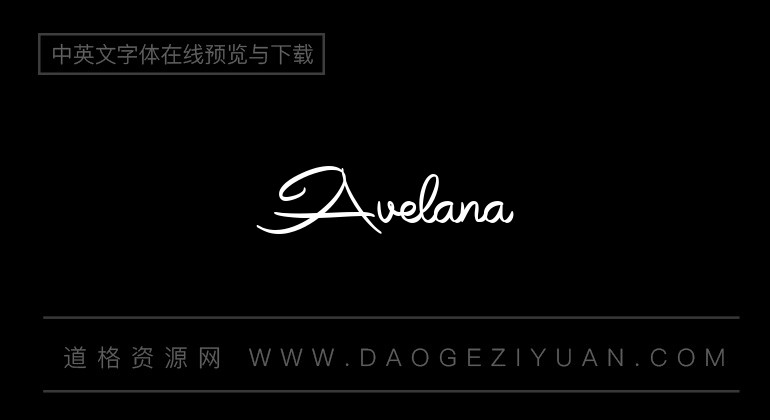
Avelana
Avelana是一种优美而现代的手写风格字体,设计师为其注入了自然、柔和、优雅的感觉。它是一种非常干净、可读性极高的字体,适用于各种设计用途,包括印刷品、品牌标识、包装设计、海报和广告等。Avelana字体家族包括正常、粗体、斜体和粗斜体四个字体样式,可以灵活地运用在设计中。总的来说,Avelana是一种非常适合那些需要表达优雅、简洁和现代感的设计项目的字体。
Avelana是一款非常不错的手写艺术字体,具有很好的视觉感,适合于文化类的宣传设计、商业类品牌的广告和产品包装设计以及个性化文字排版等较多场景。